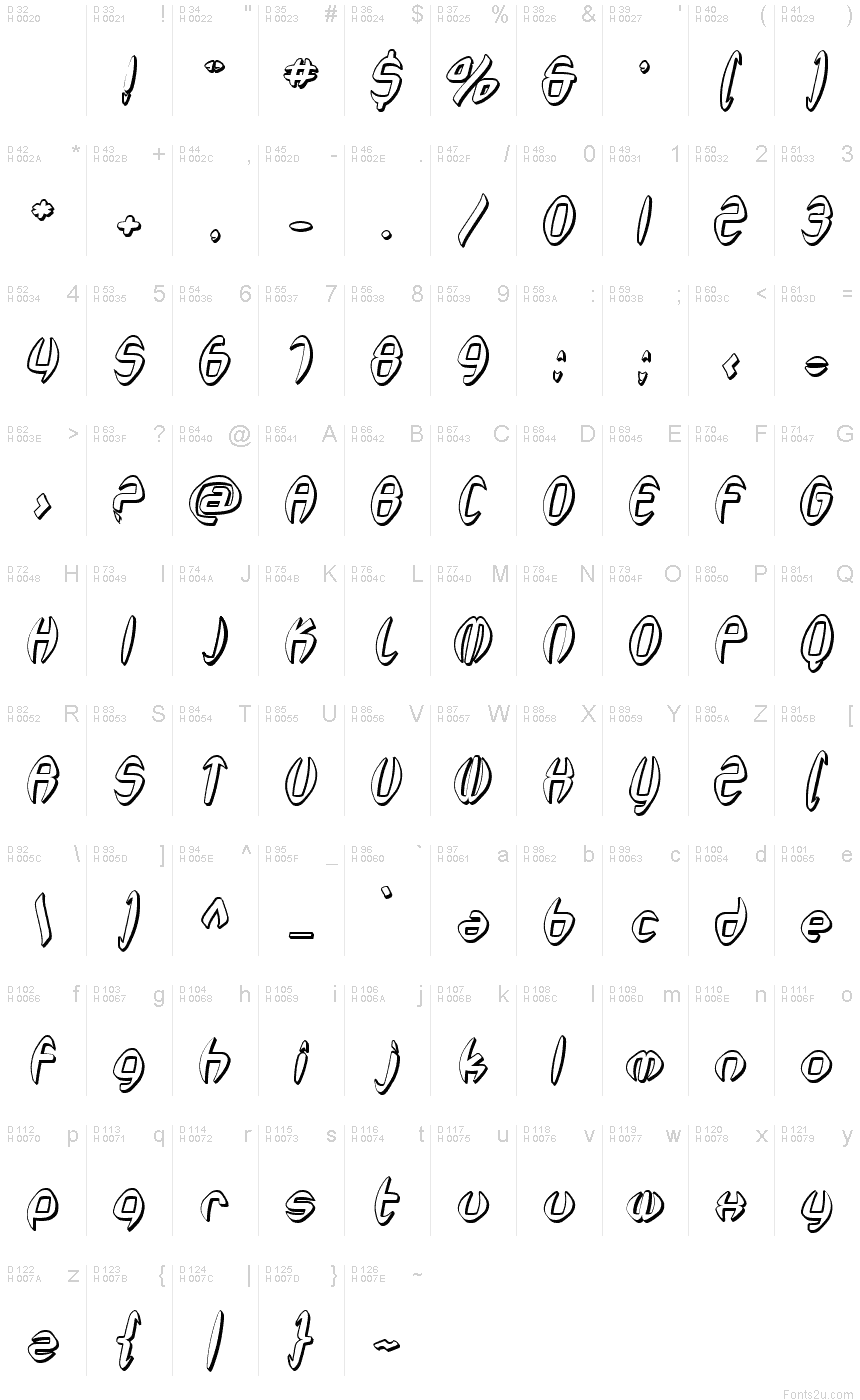
SF Synthonic Pop Shaded Oblique von ShyFoundry ist eine kostenlose, schattierte Sci-Fi-Display-Schrift mit einer gummiartigen Future-Pop-Attitüde. Die Buchstaben neigen sich und schwellen fließend an; die Kombination aus dicken Außenkonturen und innerer Schattierung verleiht der Schrift einen weichen 3D-Look, ganz ohne harte Techno-Kanten.
Sie ist ideal für Retro-Futurismus, der nicht unterkühlt wirkt: Musik-Cover, Club-Flyer, Poster-Titel, Arcade-Branding und kurze Web-Überschriften passen perfekt. Als kostenlose Schrift eignet sie sich auch hervorragend für Titelkarten, Logo-Skizzen und markante Initialen, da die abgerundeten, verzerrten Formen bereits in wenigen Buchstaben viel Charakter zeigen.
Glyphen der Schriftart SF Synthonic Pop Shaded Oblique — Basis-Lateinisch, Seite 1